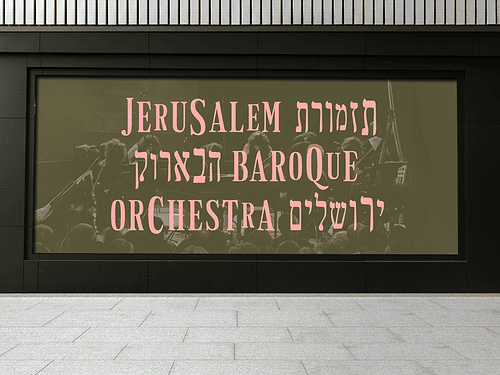
על אודות פונט פרנק־רי צר
פונט סריפי צר וקלאסי המיועד לכותרות גדולות ונועזות. הוא מתאים גם לדפוס וגם לדיגיטל, וכפונט כותרות הוא דורש את הבמה. פרנק־רי צר מבוסס על פונט פרנק־רי, שהינו גרסה מודרנית וייחודית של פונט פרנק ריהל הקלאסי. הפונט כולל נִקּוּד מֻקְפָּד וְתִקְנִי, OpenType™ Features ומערך תואם של אותיות באנגלית ותמיכה ב־219 שפות לטיניות.
סגנונות הפונט
אות מקורות, אות ראווה, אנגלית, דו־לשוני, נוסטלגי, סריף, צר, קלאסי
OpenType Features
- ליגטורות סטנדרטיות Office ← Office
- fi fl ffi ffl ff fb fj fk fl fh !!!
- ליגטורות סודיות History ← History
- רפפורט ← רפפורט
- ct אא בב גג הה חחח יי לל
- ממ פפ קק שש ששש וגם עץ אל
- מספרים של פעם 0123456789 ← 0123456789
- שברים 1/2 ← 1/2
- 123/456 ← 123/456
- חלופות הקשריות eggs ← eggs
- חלופות סגנוניות ע ← ע
- ל ← ל
- ״ ← ״
- f ← f
- ₪ ← ₪
- @ ← @
- 0 ← 0
- סוואשים ט ← ט
- Q ← Q
- אותיות מקוצרות לכותרות לץקךףן ← לץקךףן
- חלופות ליישור בלוק ﬡﬢﬣﬤﬥﬦﬧﬨ
- סמלים מיוחדים ואורנמנטים ⁕✱☺©❀§❡¶‡○▲●■®™